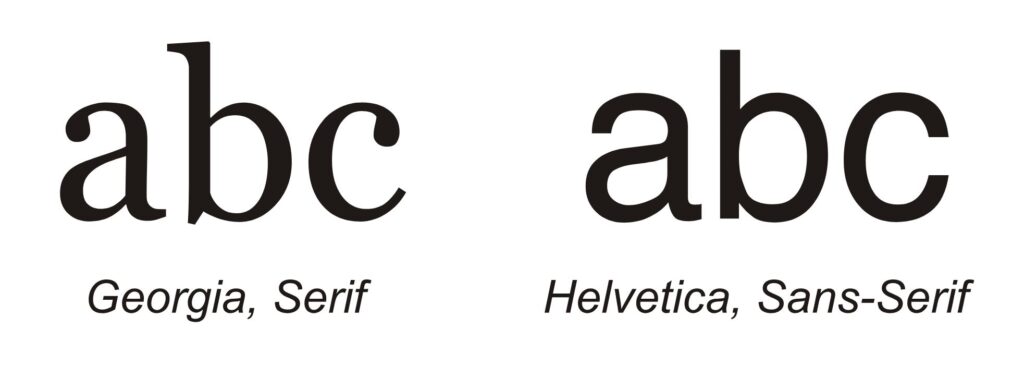
Grotesk – Serifenlose Antiqua
Serifenlose Schriften verzichten vollständig auf Serifen und zeichnen sich durch eine weitgehend gleichmäßige Strichstärke aus. Die erste bekannte Grotesk erschien 1816 durch William Caslon. Ihren Durchbruch erlebten die Sans-Serifs Ende des 19. Jahrhunderts, etwa mit der Akzidenz-Grotesk (1898). Da sie den Menschen der Zeit ungewohnt und „grotesk“ erschienen, hat sich dieser Begriff bis heute gehalten.
• Strichstärken: weitgehend gleichmäßig, minimaler Kontrast
• Serifen: fehlen komplett
• Achsen: meist senkrecht, neutral
• Proportionen: kompakt, funktional, klar strukturiert
• Gestaltung: schlicht, nüchtern, sachlich
• Wirkung: modern, direkt, sachlich → sehr gut für Plakate, Werbung, Schilder